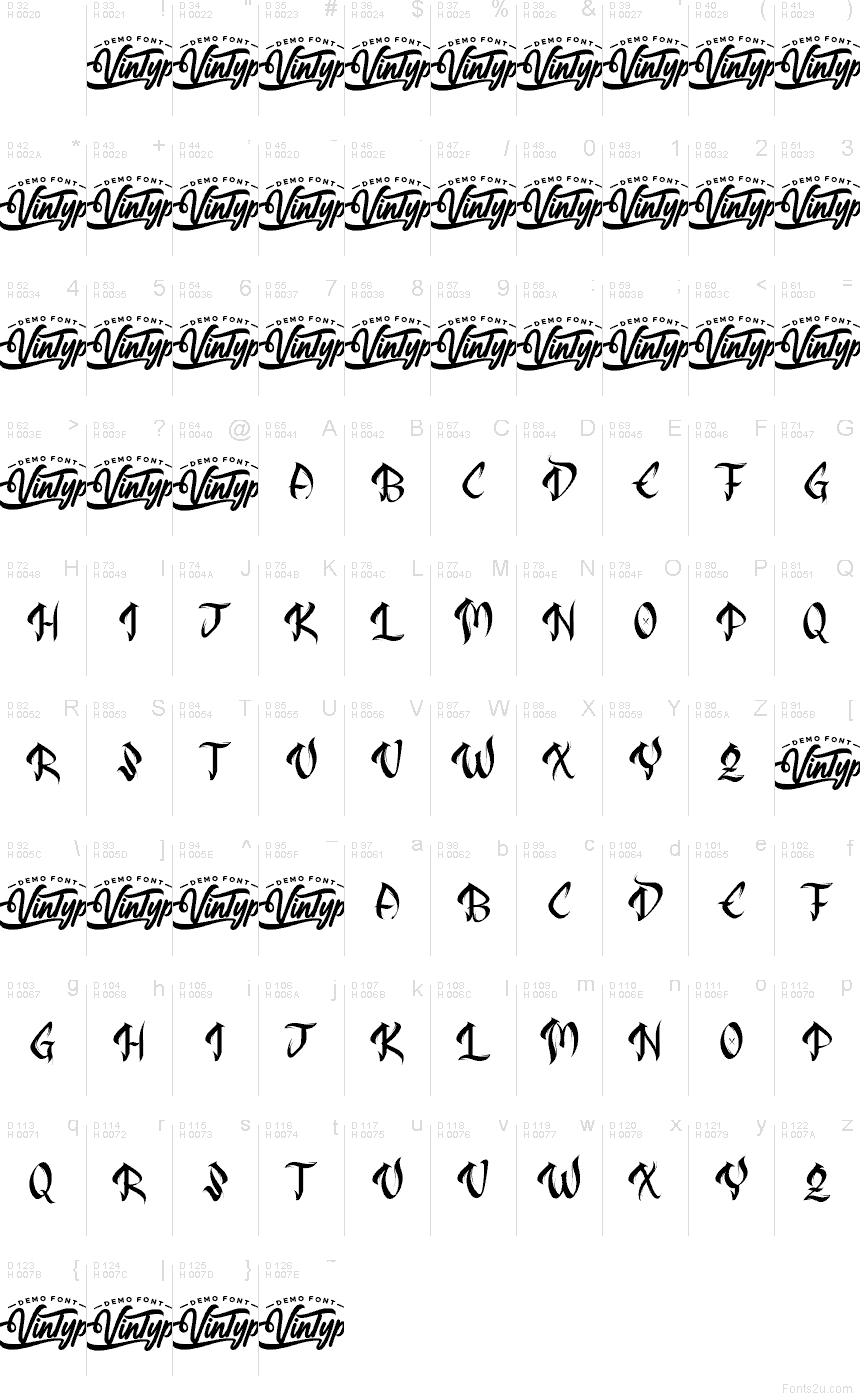
Bad Rocker di VinType Studio è un carattere gotico gratuito in maiuscolo con un battito blackletter e un ritmo affilato, quasi come una lama. Le lettere fondono curve voluminose e tagli interni decisi, per un mood che evoca più il poster di un concerto rock che un revival medievale, con un tocco inquieto e disegnato a mano che attraversa tutto il set.
È ideale per il branding musicale, titoli di poster, copertine di album, merchandise a tema tattoo o grafiche per locali e festival dove serve un carattere gratuito che abbia carattere senza sembrare antico. Usalo per brevi titoli, scritte d'apertura e monogrammi: i tratti ricurvi e le giunture appuntite danno abbastanza grinta anche a poche lettere per farsi notare sulla pagina.